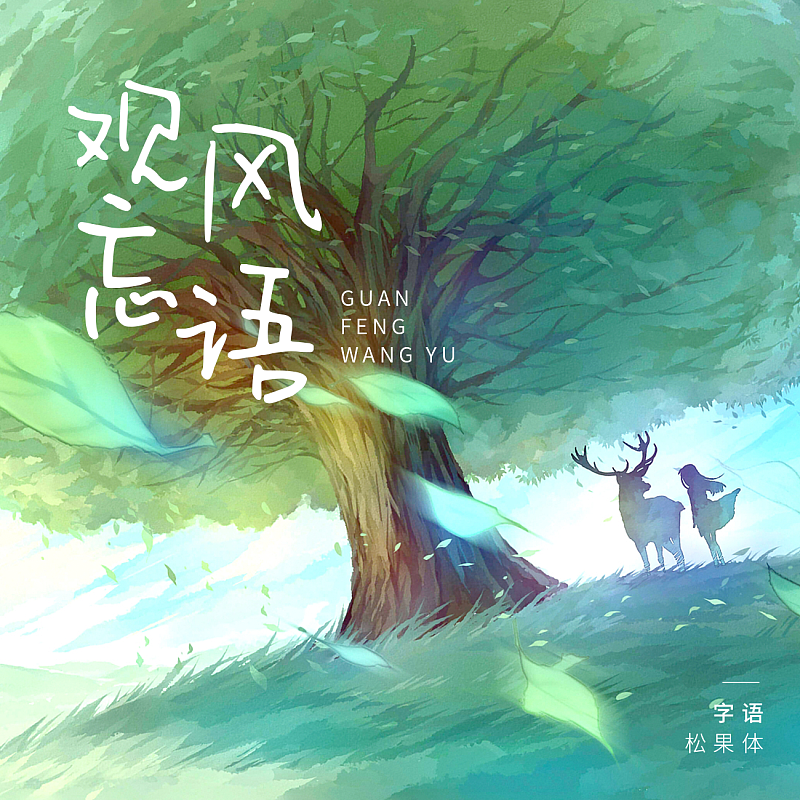
字語松果體
松果體這款字是一款風(fēng)格可愛的手寫體,字體筆畫簡單直接,該字跳動的旋律感,及搖曳生姿的字形,童趣可愛,自在隨性,由內(nèi)而外的歡喜。適用于文藝類的書刊,少年兒童類的書刊,品牌廣告和產(chǎn)品包裝設(shè)計等。
字體風(fēng)格:廣告字體, 硬筆手寫
字體用途:廣告, 正文, 報刊, 動漫